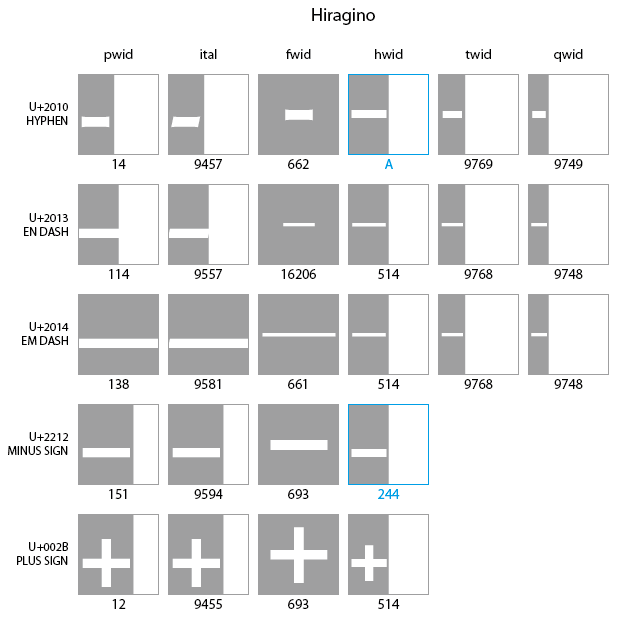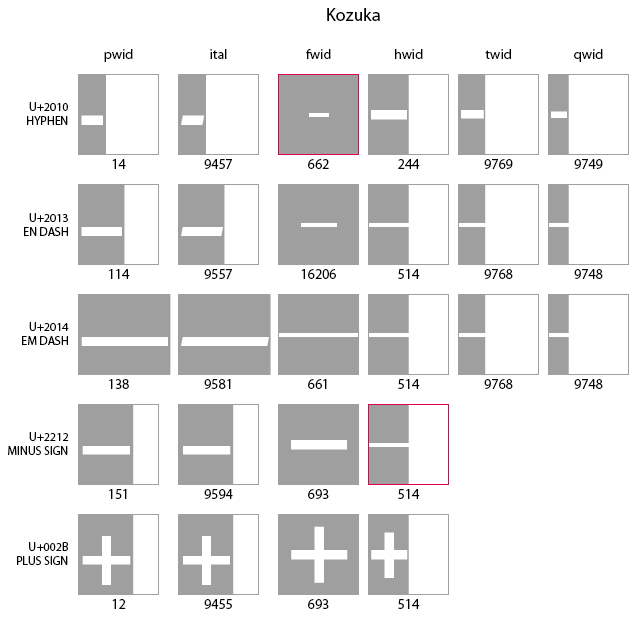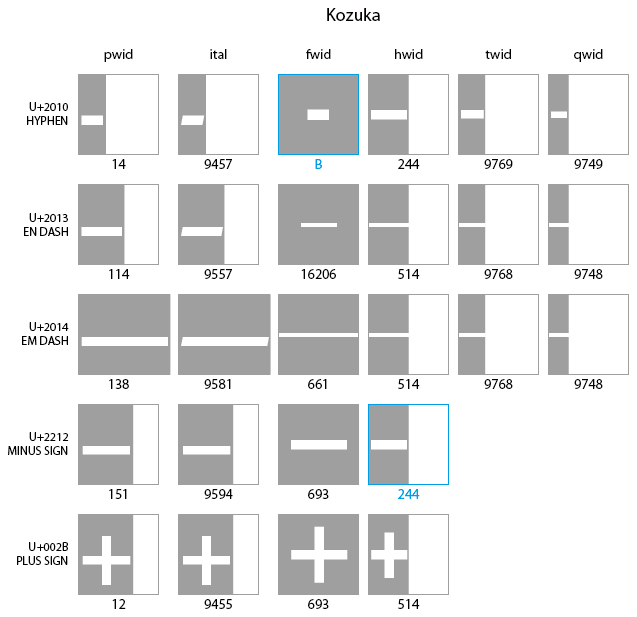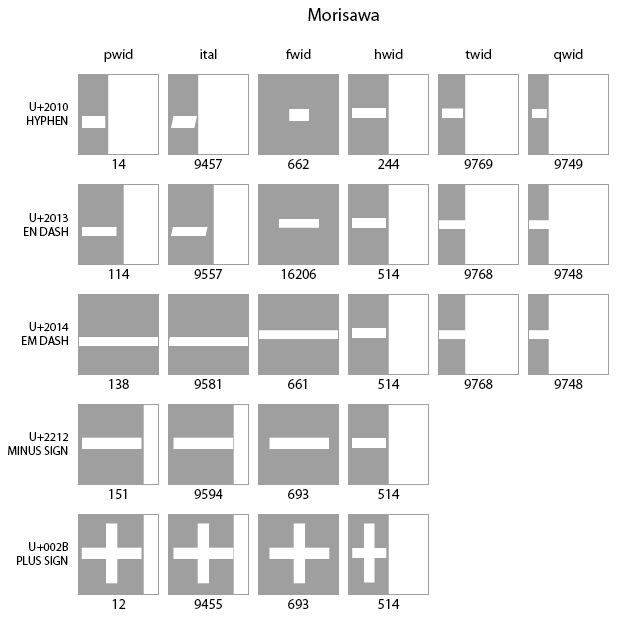
ハイフンの仲間たちの混乱
- Adobe-Japan1-7に向けて以前書いたことを蒸し返してみるシリーズ、第2弾。横棒型のグリフをめぐる混乱について。以下の図は、ハイフン、ENダッシュ、EMダッシュ、マイナス記号、プラス記号を入力し、左からプロポーショナル(pwid)、イタリック(ital)、全角(fwid)、半角(hwid)、三分(twid)、四分(qwid)のタグを適用したもの。グレー地は文字幅。正方形の枠は全角の目安。
- 下図はヒラギノ。「ハイフンの半角字形」と「マイナス記号の半角字形」(赤枠)のデザインが、他と揃っていない。
- これを直してみたのが、下図。まず、「ハイフンの半角字形」には、適切なグリフが存在しない。CID+244はハイフンとマイナス記号に共通の半角グリフであるため、ヒラギノのように両者のデザインを区別する体系では、無理が生じてしまう。この問題を解決するためには、「ハイフン専用の半角字形」(下図A)を追加する必要があると思う*1。もう一方の「マイナス記号の半角字形」については、ヒラギノに限らずCID+514ではなくCID+244とするのが適切だと思う。が、互換性を損ってはまずいので、GSUBテーブルを修正しろと言うつもりはない。
- 次に小塚書体について見てみる(下図)。「ハイフンの全角字形」と「マイナス記号の半角字形」(赤枠)のデザインが、他と揃っていない。
- これを直してみたのが、下図。「ハイフンの全角字形」の不整合は、まあ、わざとなのかもしれないけれど、「細くない全角ハイフン」(下図B)が存在しないのは、やはり気持ち悪い気がする*2。「マイナス記号の半角字形」については、ヒラギノの項で述べたとおり。
- ちなみにモリサワフォントは、横棒型のグリフ群のデザインにおいて(たとえばCID+514とCID+244のグリフを共通とするなど)区別の少ないシステムを採用しており、現状でも整合性を保っている(下図)。